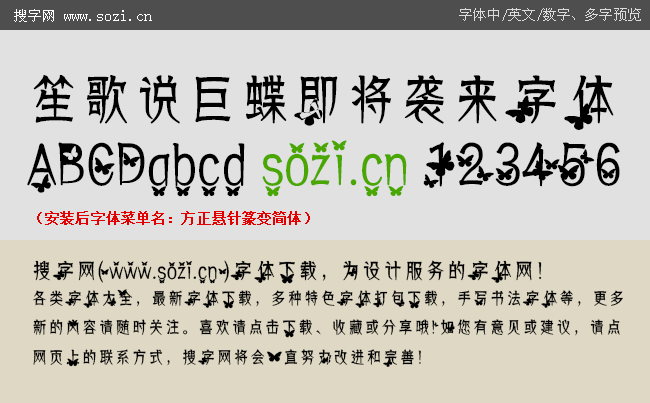
笙歌說巨蝶即將襲來字體
搜字網(wǎng)給大家提供一款笙歌說巨蝶即將襲來字體手機(jī)中文字體下載。這款手機(jī)字體是在方正懸針篆變簡體筆畫間插入了漂亮的蝴蝶等卡通圖案。方正懸針篆變字體意在保留篆書韻味,同時將隸書與楷書筆畫特征熔于一爐,實(shí)為三種書體的統(tǒng)一。將傳統(tǒng)書法藝術(shù)與現(xiàn)代形式語匯融合,追求裝飾性及藝術(shù)美感,端莊秀美、開張疏朗,雍容大氣、復(fù)古卻易讀。加入了卡通圖案后又增添了趣味性,特別適合喜歡手機(jī)字體個性一些的朋友在手機(jī)上安裝使用。